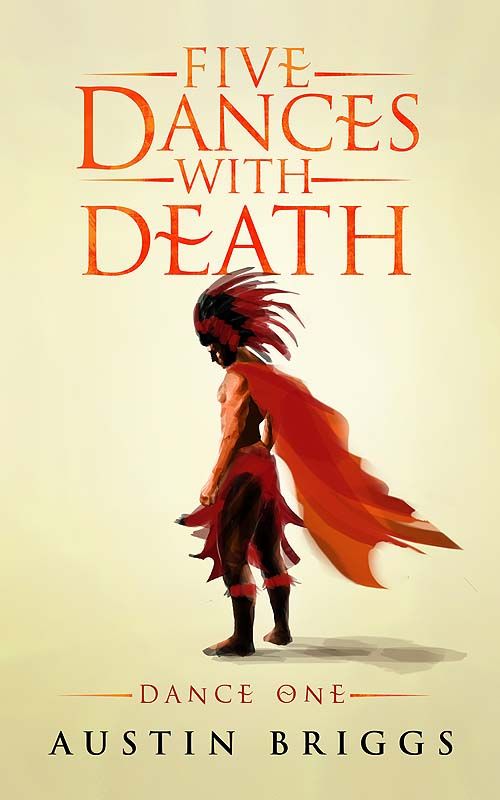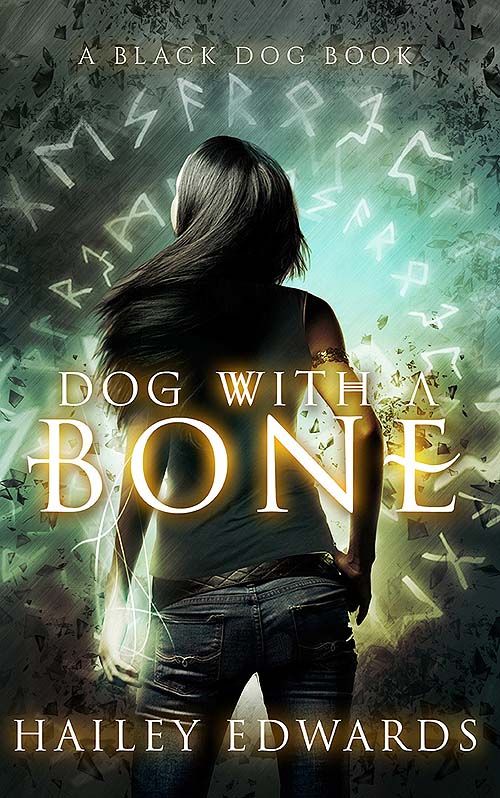
Foro de Tipografía ¿Qué tipografía es? el 23.05.2015 a las 19:52 por Usuario desconocido · 6 comentarios Seguir este tema Dejar de seguir este tema 2 seguidores Me gustaría saber si la letra E es de la tipografía o esta modificada a mano. Comentar Me gusta
La tipo es L’Elf Noir du Mal.
Gracias avaphics, Anavio me gusta. Yo subí la "E" sola a "WhatTheFont" y claro no me daba ningún resultado. Pues he visto varias portadas con la E modificada de la misma manera, así que será que se copian.
Me perece que es esta, pero la letra "E" la han modificado.